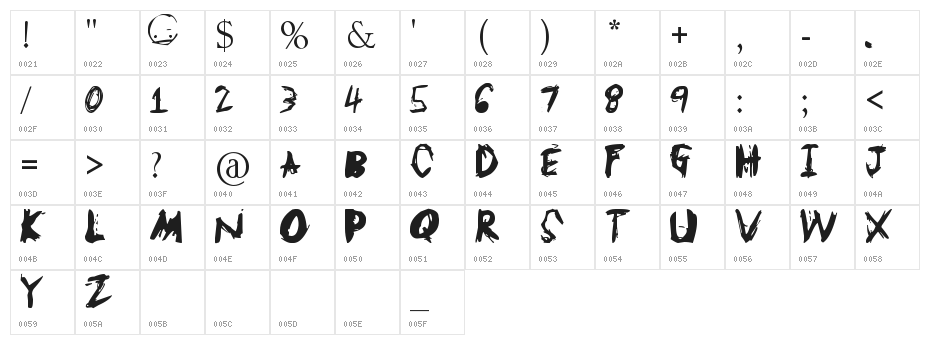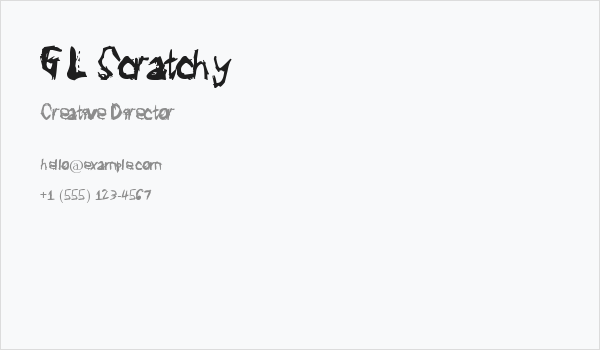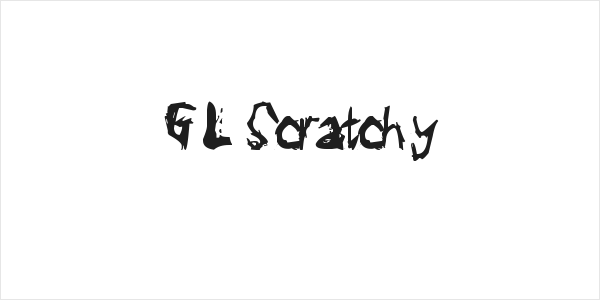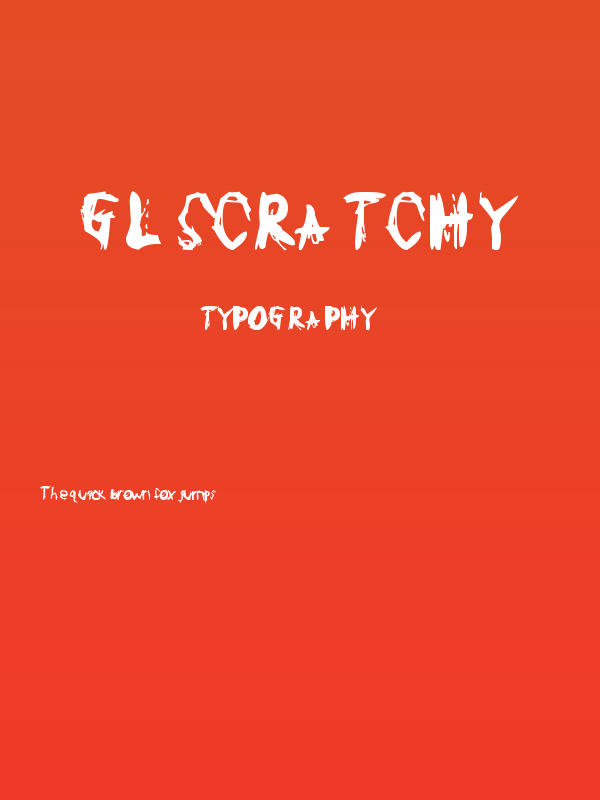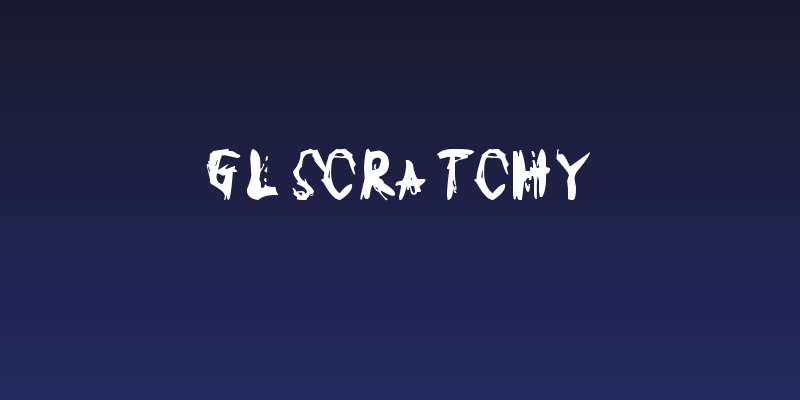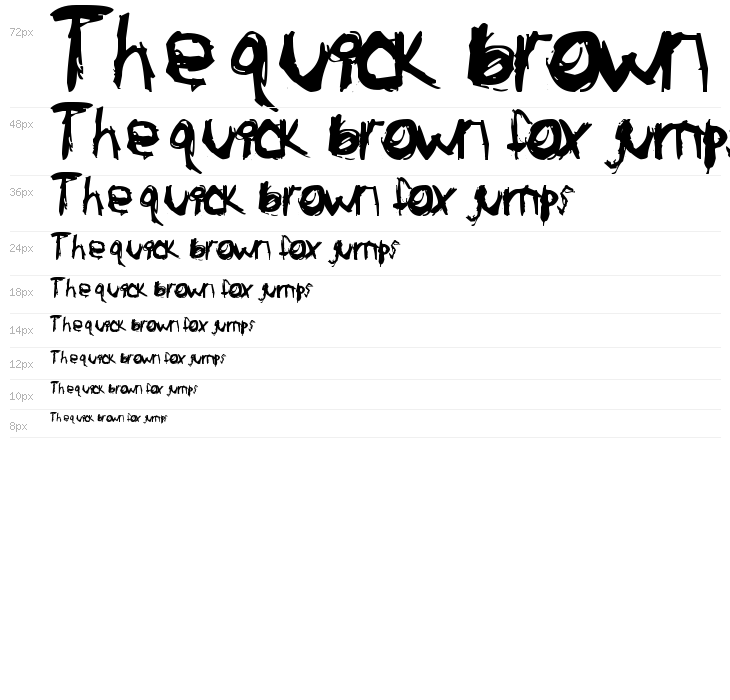
GL Scratchy Font
| Gesamtstil | Grunge, Rebellious |
| Vorgeschlagene Projekte | Music album covers, edgy posters, alternative branding, streetwear designs. |